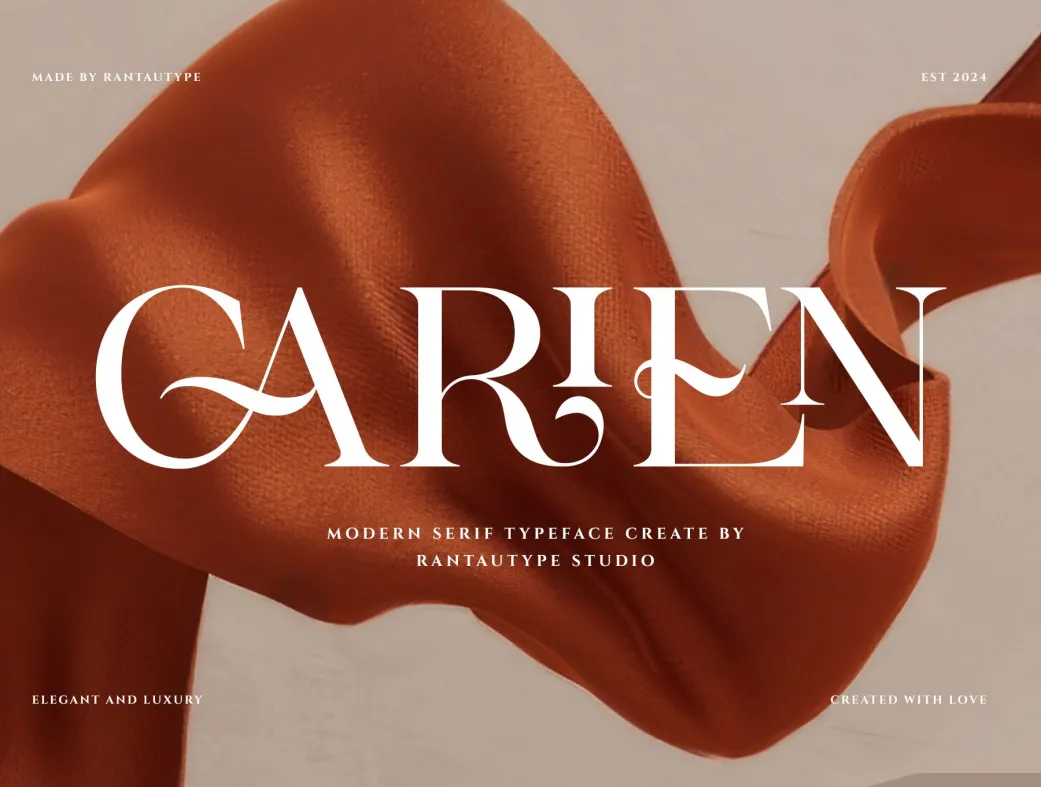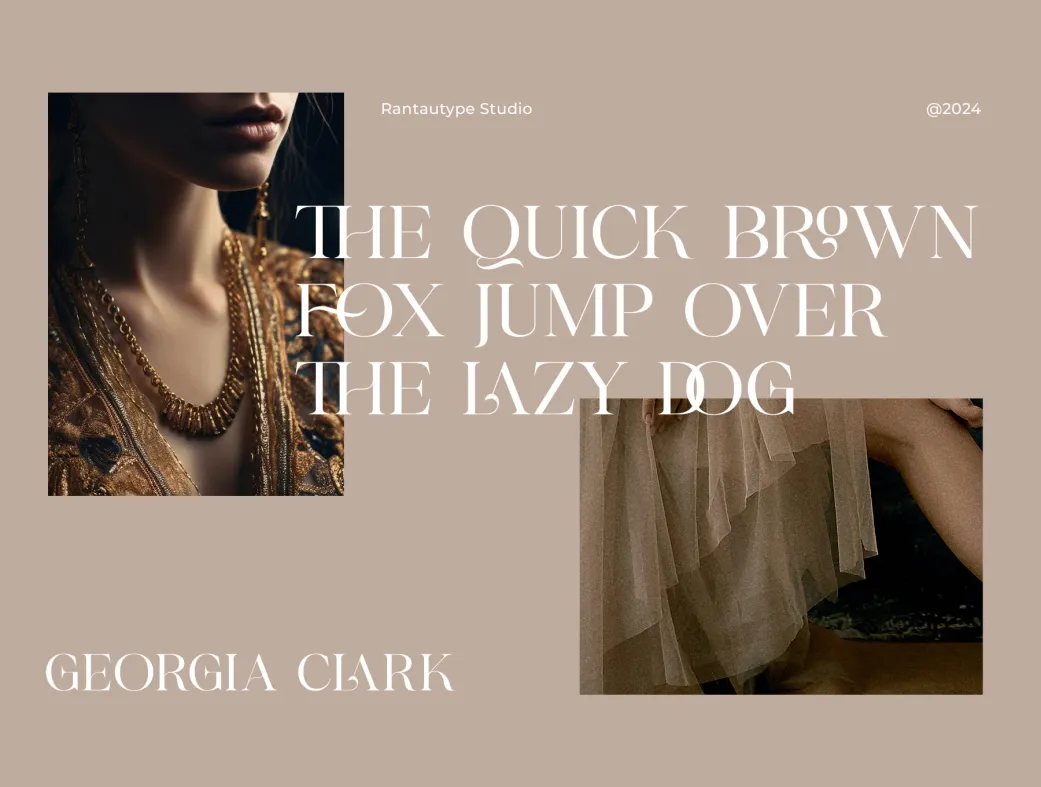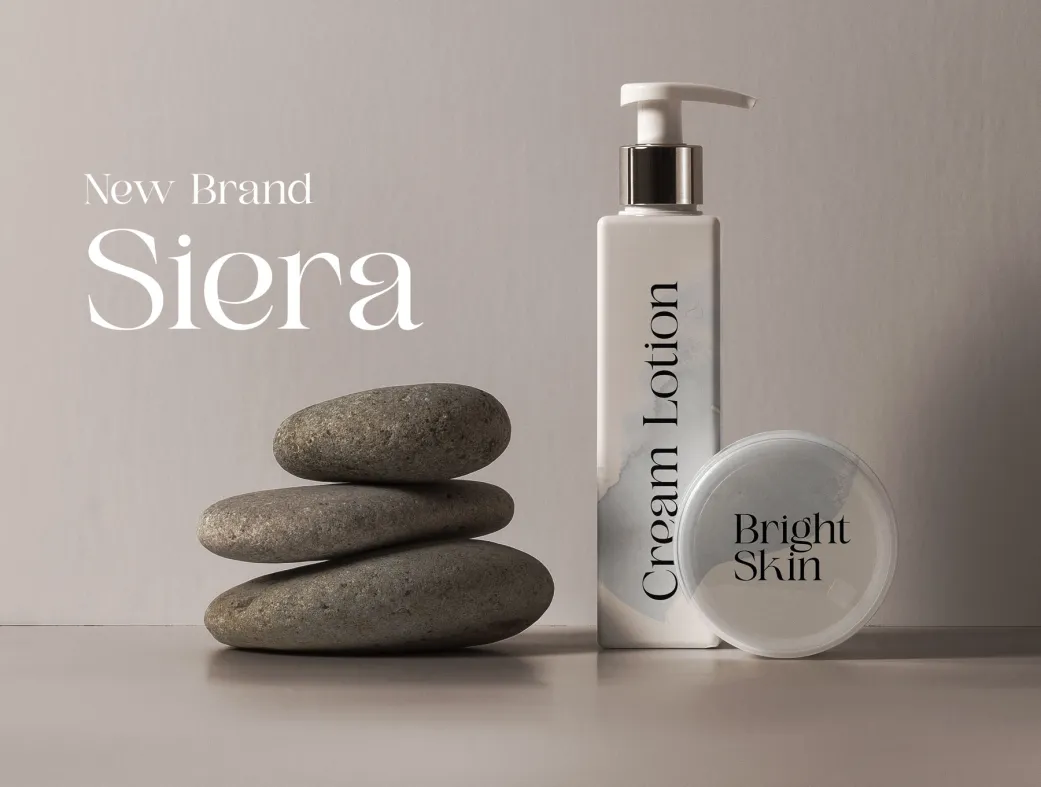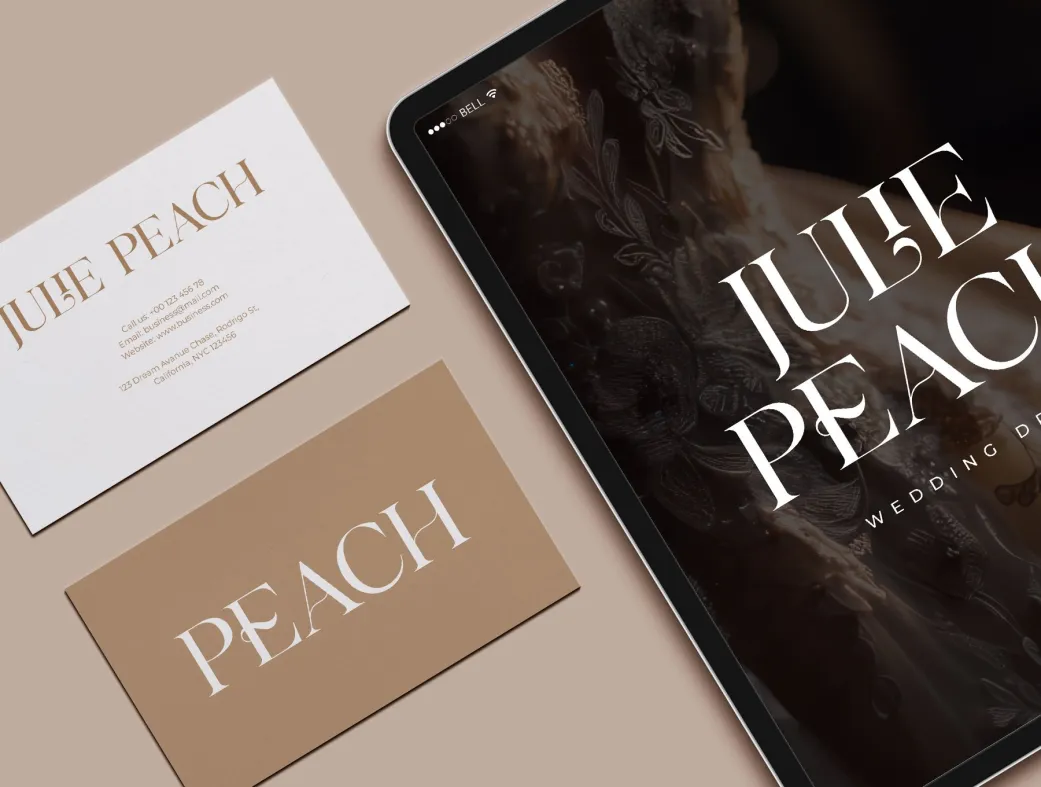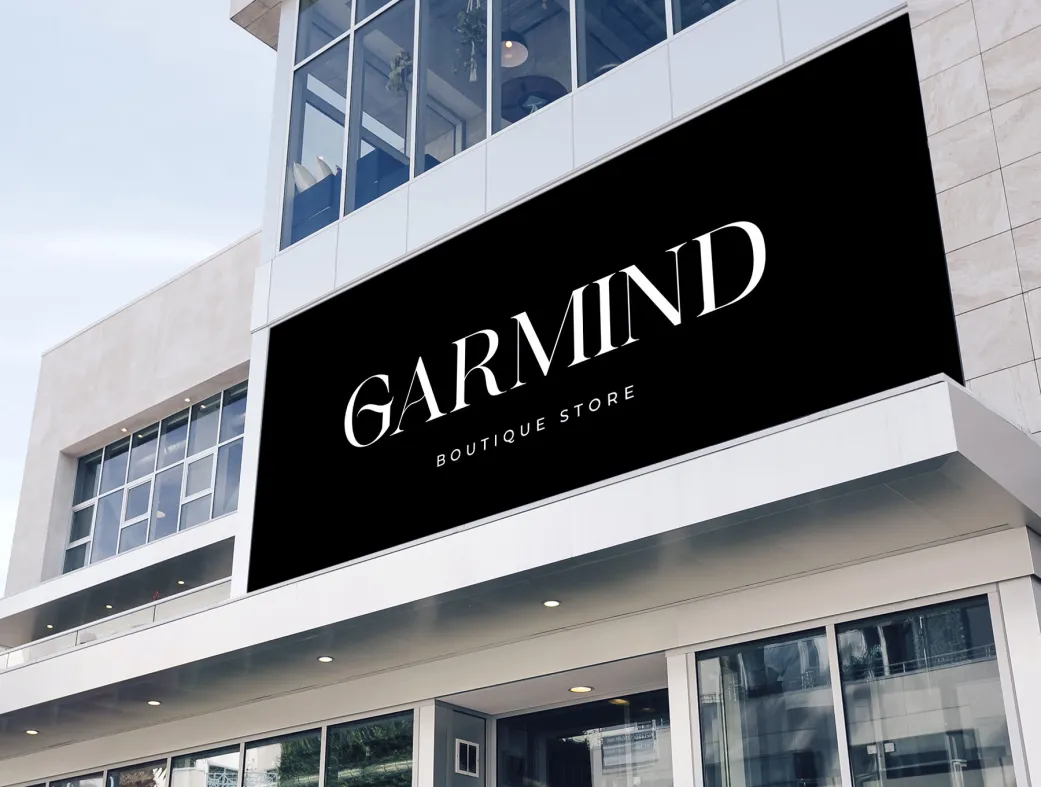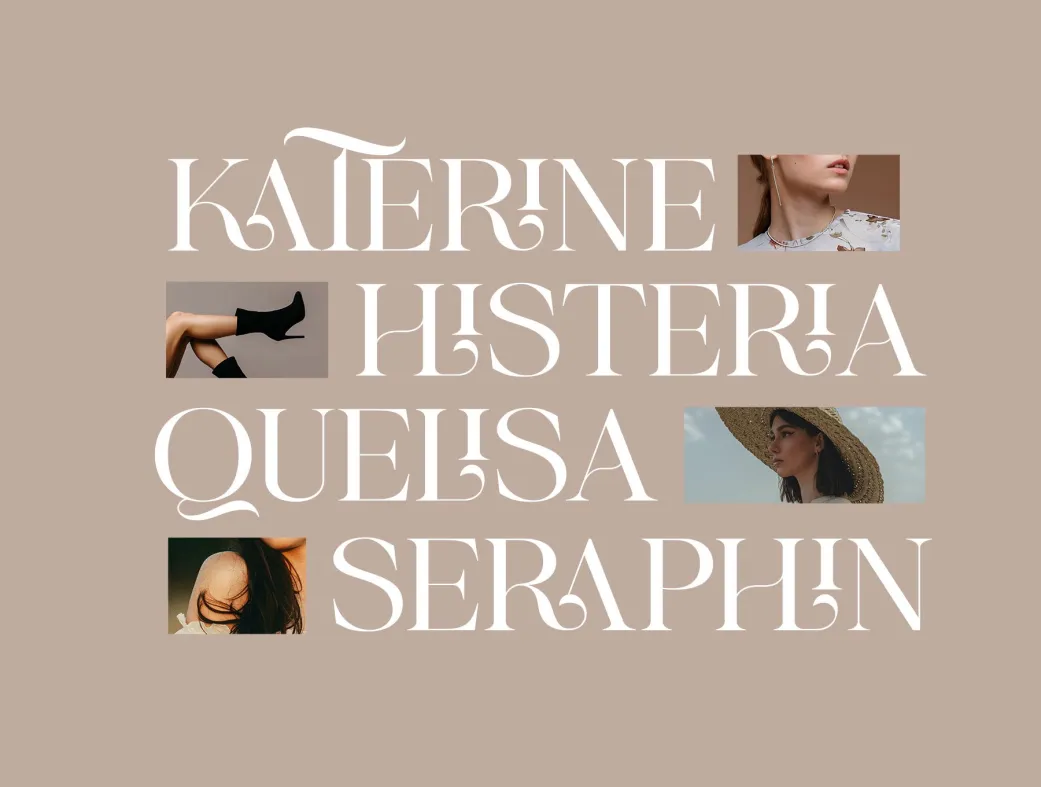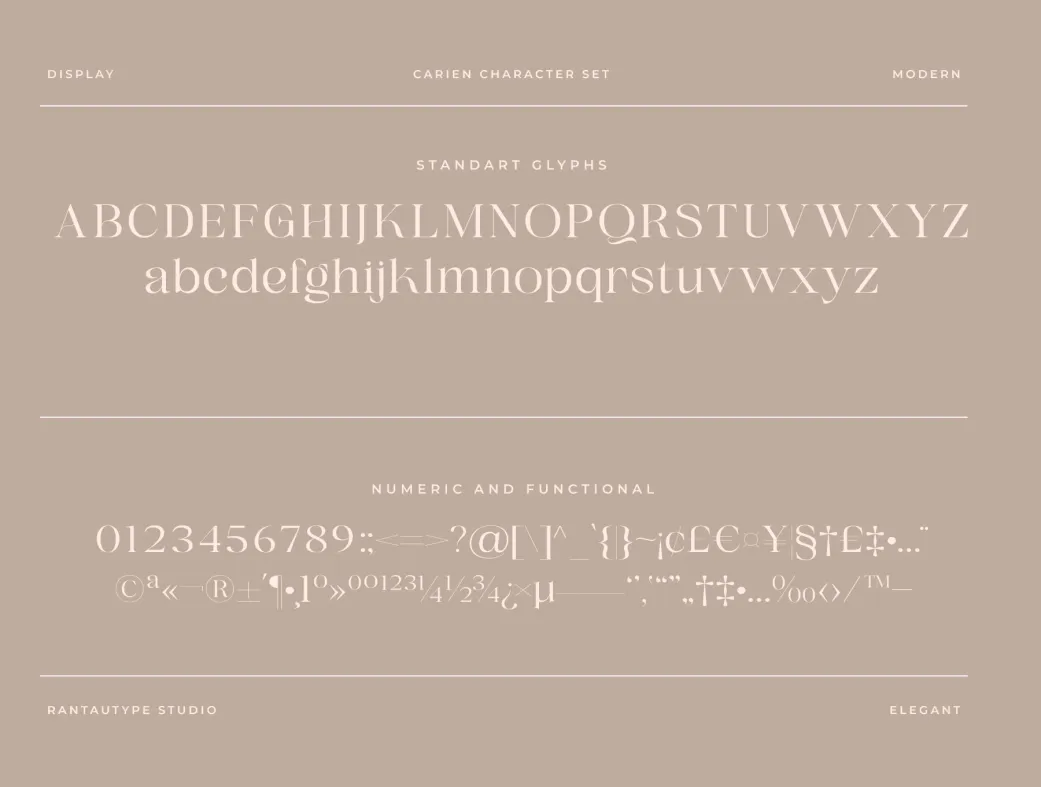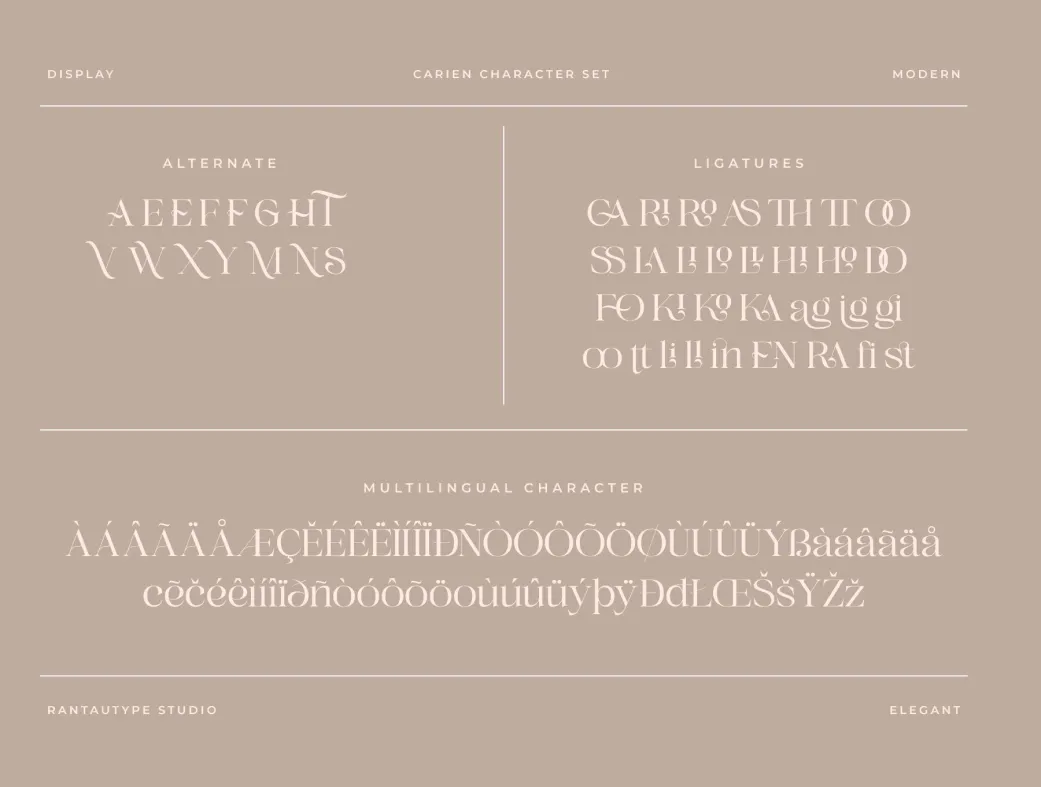
فونت سریف مدرن کارین | Carien
به دنبال زیبایی و ظرافت در طراحی هستید؟ فونت سریف مدرن کارین، با منحنی‌های لطیف و جزئیات دقیق، پروژه‌های شما را متمایز می‌کند!
Carien A Modern Serif Font
معرفی محصول:
فونت سریف مدرن کارین (Carien) یک فونت زنانه و نمایشی است که به زیبایی و ظرافت می‌بالد. منحنی‌های لطیف و جزئیات دقیق آن حس شیک و زنانه‌ای را منتقل می‌کند. این فونت به شما کمک می‌کند تا پروژه‌های طراحی بصری خود را به شیوه‌ای خاص و متمایز ارائه دهید.
ویژگی‌ها و مزایا:
فونت کارین یک انتخاب ایده‌آل برای هر پروژه خلاقانه، طراحی‌های شیک و مرتبط با سبک زندگی است. از جمله کاربردهای آن می‌توان به طراحی لوگو، تبلیغات، واترمارک بر روی عکس‌ها، نوشت‌افزار، پروژه‌های برندینگ، مجلات، دعوت‌نامه‌ها، برندهای شرکتی، طراحی محصولات، برچسب‌ها و پروژه‌های تجاری دیگر با لمسی از ظرافت اشاره کرد.
کاربردها و نکات استفاده:
اگر شما یک طراح حرفه‌ای هستید یا تازه‌کار در زمینه طراحی گرافیک، فونت کارین می‌تواند گزینه‌ای عالی برای شما باشد. این فونت با طراحی زیبا و شیک خود می‌تواند به راحتی در پروژه‌های مختلف مانند طراحی وب‌سایت، کاتالوگ، بروشور و... مورد استفاده قرار گیرد. همچنین، با توجه به چند زبانه بودن این فونت، می‌توانید از آن در پروژه‌های بین‌المللی و چند زبانه استفاده کنید.
2. این فونت چند زبانه است؟
بله، فونت کارین شامل کاراکترهای چند زبانه است و می‌تواند در زبان‌های مختلفی مانند انگلیسی، اسپانیایی، آلمانی و... مورد استفاده قرار گیرد.
4. آیا فونت کارین شامل حروف جایگزین و لیگاتور است؟
بله، فونت کارین شامل حروف جایگزین و لیگاتور می‌باشد که به شما امکان می‌دهد طراحی‌های خود را با تنوع بیشتری انجام دهید.